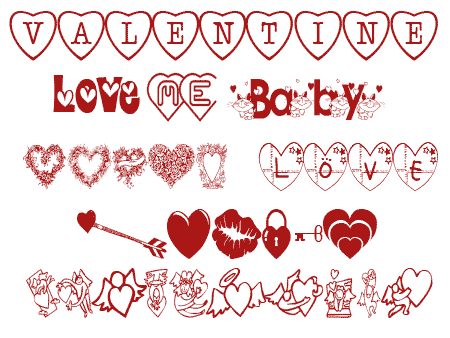
Шрифт - День Влюбленных
Шрифт для создания Валентинок.
Пишет только английскими буквами. Есть шрифты, где можно писать слова, а есть такие, где вместо букв появляются картинки.